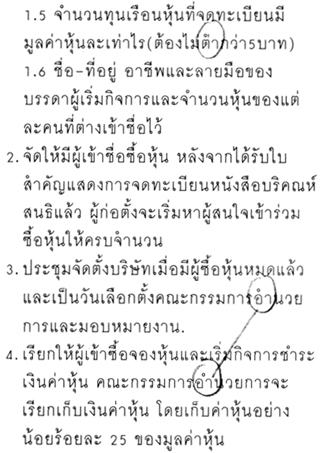
ฟอนต์ไม่เหมาะ
ผมรู้ ว่าการวิจารณ์น่ะดี
ผมก็จบออกแบบมา ผ่านการศึกษาด้วยการวิจารณ์งาน
ผมก็รู้ว่า ความเห็นเป็นเรื่องปัจเจก
แต่ไม่รู้จะอธิบายยังไงดี
เอางี้
อ้างอิงจมล ที่ผมเขียนถึงยักษ์เลยนะ (ถ้าเห็นควรไม่ด้วย บอกให้ลบได้ครับ)
อ้างอิงจริงๆแล้วกลัวว่าจะเกิดเหตุการณ์อย่างนี้น่ะ
เจ้าของงานมาอ่านเจอแล้วคิดว่า
เออ ขอไข่มองเหมือนยอยักษ์จริงด้วยแฮะ
ไอ้สีฟ้าๆนั่นก็อ่านยากจริงๆด้วย
อ้อ ฟอนต์นี่ชื่อกิติธาดาเรอะ เวลามันใหญ่ๆ อ่านลำบากแฮะ ไม่มีฟอนต์อื่นเหรอ
เรื่องฟอนต์รึเราก็ไม่มีความรู้
ทำไมไอ้คนออกแบบมันไม่ระวังให้เราวะ
เอางี้ละกัน งานหน้าไม่ให้มันทำแล้ว ทำงาน...นี่หว่า
ให้ไอ้แอนนี่แหละทำ มันเก่งดี
ประมาณนี้น่ะ
เพิ่งคุยกับเลย์ไปตะกี้ ก็เพิ่งคิดออกว่าจะอธิบายยังไงให้เข้าใจ
ว่าที่เป็นห่วงน่ะ มันเรื่องอะไร)
พอเป็นเรื่องงาน ทำมาหากิน ก็จะมีมุมมองของเรื่องชื่อเสียงและอื่นๆมาประกอบให้ต้องพิจารณาด้วย
แค่นี้แหละครับ
มันป่องไปนิดนึงนะ 555
ฟอนต์Tahomaไม่เมาะกับบอร์ดนี้ครับ
ควรเปลี่ยนเป็น iannnnn ISO
1. งานนี้เป็น Design ของทางเมืองนอก เขาไม่รู้ภาษาไทยแต่เขาต้องเป็นผู้ออก ArtWork มาให้
โดยให้ทางไทยส่ง ตัวHeadline ที่ createOutline แล้วไปให้เขาจัดวาง LayOut
2. LayOutต้องถูกทำตามคู่มือภาพลักษณ์องค์กร (Corporate Identity) ที่มีกฏระเบียบการใช้
3. fontที่ถูกเลือกให้เป็นfontขององค์กรคือ Kittithada ของค่าย PSL ซึ่งทั้งเอเจนซี่และองค์กร
ต้องซื้อไลเซ่นที่ถูกต้องจากPSL
4. สีที่ใช้ได้ ต้องเป็นสีตามนั้น คือตามคู่มือ(ภาพทำมาจากเมืองนอก)
5. เปอร์เซนต์ของขนาดตัวหนังสือ ภาพ ฉากหลัง ความชัดและไม่ชัด ตามคู่มือ
6.สำนวนการเขียนต้องมี we, you หรือ คุณ, เรา เช่นนี้เสมอ (ถ้าไม่ใช่งานโปรโมชั่น)
7. งานนี้ด่วนและไม่มี ArtDi ดูแลให้ตั้งแต่ต้น เพราะทำมาจากเมืองนอก
8. ผมถูกเรียกให้ไปช่วยดูว่างานนี้เรียบร้อยดีหรือไม่ ในฐานะ ArtDi ที่เคยทำงานให้กับองค์กรนี้
9.ปัญหาที่คาดว่าน่าจะมีคือเรื่องโลโก้ที่ตามคู่มือแล้วมันจะเล็กมากเมื่ออยู่บนตึก
ตัวอักษรก็จะเล็กและจม อ่านยาก เราจึงเสนอว่าต้องโกงจากคู่มือบ้าง อย่าทำตามเป๊ะๆ
10.การแก้ปัญหาเฉพาะหน้าคือ เปลื่ยนcropภาพ ขยายโลโก้และตัวอักษร ให้พอจะดูเหมือนในคู่มือ
เราจัดการแก้ไขใหม่และส่งกลับไปทางเมืองนอกให้เขาอนุมัติแบบ
โดยแจ้งเหตุผลที่ปรับแก้ไขไป และเขาก็ OK ให้ผลิตได้
11.วัสดุที่ใช้เป็นรูพรุน เพื่อให้คนในตึกมองออกนอกหน้าต่างได้ การที่เป็นรูพรุน ทำให้สีของภาพ
หายไป ซีดไป จางไปส่วนหนึ่ง และเมื่อต้องอยู่กลางแจ้ง การซีดการจางของภาพ จะเพิ่มขึ้น
เป็นสองเท่า ดังนั้น การผลิดต้อง Make Over ยิ่งขึ้นไปอีก คำถามคือแค่ไหนมันจะออกมาพอดี?
12. ผมและทีมงานพร้อมกับลูกค้าไปดูปรู๊ฟสีงานInkJet ที่บริษัทผู้ผลิตป้าย และปรับแต่งแก้ไขสีกันหน้าเครื่อง
13. ในส่วนภาพพอจะเร่งเข้มขึ้นได้ แต่ในสีตัวอักษร ไม่สามารถทำได้มากนักเนื่องจากจะผิดไปจากคู่มือ และทีมที่ไปช่วยกันดูก็เห็นพ้องกันในแบบที่ปรับแต่งแก้ไขสีที่เผื่อเอาไว้ จึงสั่งผลิตจริงได้ทันที
14. เมื่อป้ายจริงขึ้นที่ตึก ผมกับทีมงานออกไปดูของจริง และแจ้งให้ทางผู้ผลิดป้าย ปรับการขึงการติดตั้ง จนเรียบร้อยดี
15. กับปัญหาที่แก้ไขไป มันออกมาได้แบบนี้ ทุกคนก็รับได้ OKกับมัน ที่ไม่OK ก็มีบ้างในบางจุด
เหมือนที่หลายๆคนมองเห็นเช่น ตัวหนังสืออ่านยากไปมั้ย สีจมไปมั้ย? แต่ทีมงานก็ รับได้เพราะรู้เงื่อนไขต่างๆ ที่มาที่ไปของมัน ตรงข้าม กลับรู้สึกว่า ดีนะที่แก้ไขกันไว้ก่อนบ้าง
16. ทางเมืองนอกเขาก็OK แฮปปี้กันทุกฝ่าย...เรื่องก็จบลงด้วยดี
ผมเคยเห็นเหมือนกันที่บริษัทเดิมที่ผมเคยทำงาน (มาเดือนกว่าๆ แล้วติดทหาร :08:)
เขาล็อคสเปกมาในเอกสารแนบเรียบร้อยเลยว่า ฟอนต์ที่ใช้ ห้ามกว้างกว่านี้
สีก็ต้องห้ามหลุดไปจากนี้ อาร์ตไดเรกชั่นต้องเท่านี้เท่านั้น เป๊ะๆ ห้ามยุกยิก
เรียกได้ว่าเราแทบจะไม่ได้ออกแบบเองเลย (ทั้งๆ ที่จ้างเราออกแบบนะ)
เพราะการกำหนดมาของบริษัทแม่ซึ่งซีเรียสกับภาพลักษณ์องค์กรมากๆ
เลยเว็บนั้นกลายเป็นเว็บที่ออกมาแข็งทื่อมะลื่อไป
นี่อาจเป็นความแนวอย่างนึงก็ได้
post ให้ดูกันแบบขำๆ แต่ได้ความรู้กลับมาเพียบเลย
รู้สึกเหมือนย้อนกลับไปเป็นนิสิตตอนนั่งเรียน environmental graphic อยู่ในห้องเลคเชอร์
ตอนนั้นเป็นช่วงเลือกตั้งผู้ว่า กทม เลยได้นั่งวิเคราะห์ป้ายหาเสียงกันอยู่เกือบทั้งเทอม
ของแต่ละอย่าง มีที่มาจริงๆ
คงไม่ถึงกับฟอนต์ไม่เหมาะ แค่สงสัยว่าทำไมเป็นอย่างนั้นได้
จากนิตยสาร oom อุ้มโฉมใหม่หลังจากที่หายจากแผงหนังสือไปนานนนนน
มี อ.โรจ นั่งเท่อยู่ในเล่มด้วยนะ
เห็นน้องที่จัดอาร์ตเวิร์กแล้วสงสารครับ งานหนักสุดๆ :05:
ได้วิเคาะห์ของชูวิทย์มั่งป่าว  :30:
ครั้งแรกที่ได้ทำงานใหญ่ขนาดนั้น ตอนนั้นยังเรียนอยู่เลย
งั้นดูอันนี้ รู้สึกไม่เหมาะตรงไหนไหมครับ  :27:
ไม้หันอากาศมัน
อ๊ะ
ไม่ใช่สิ